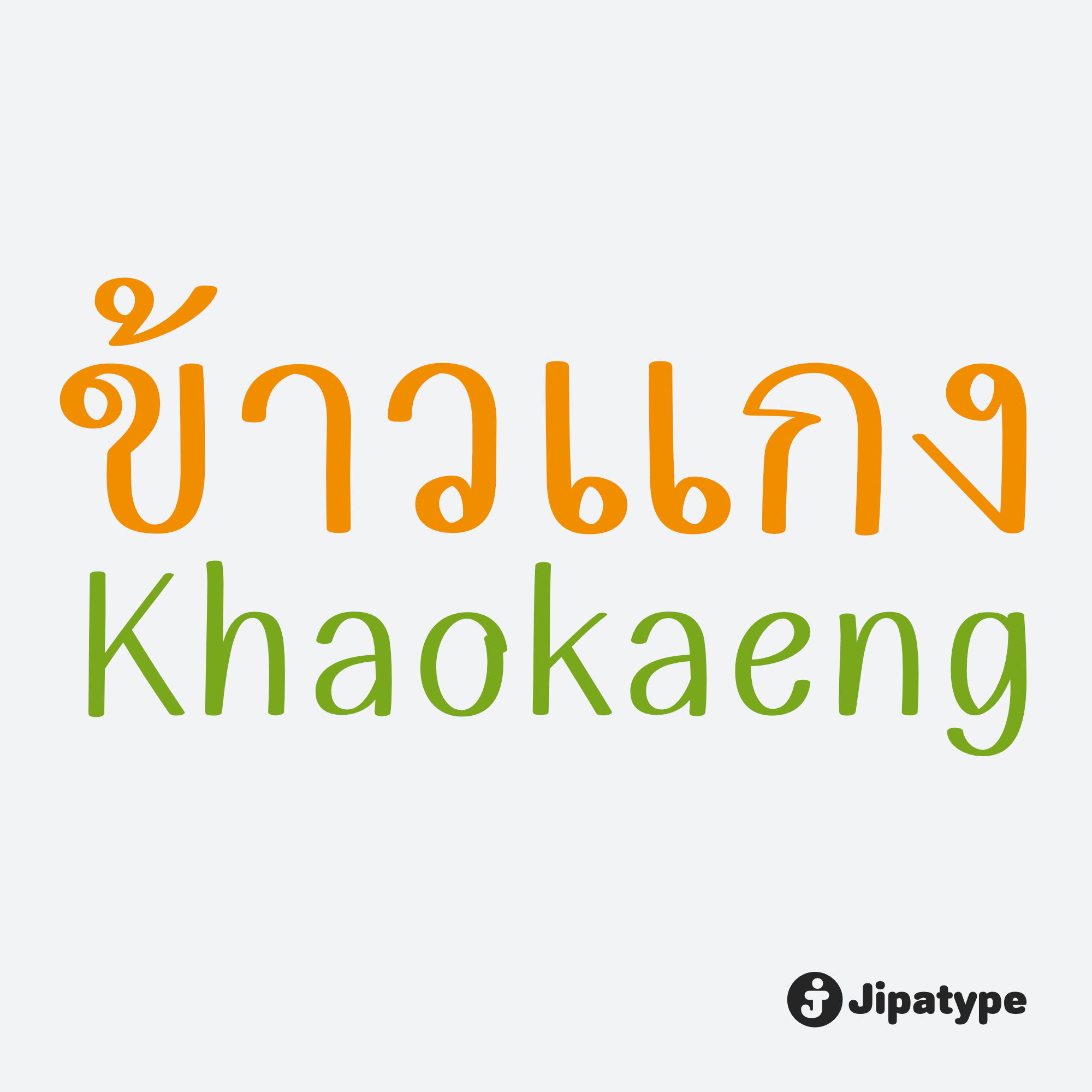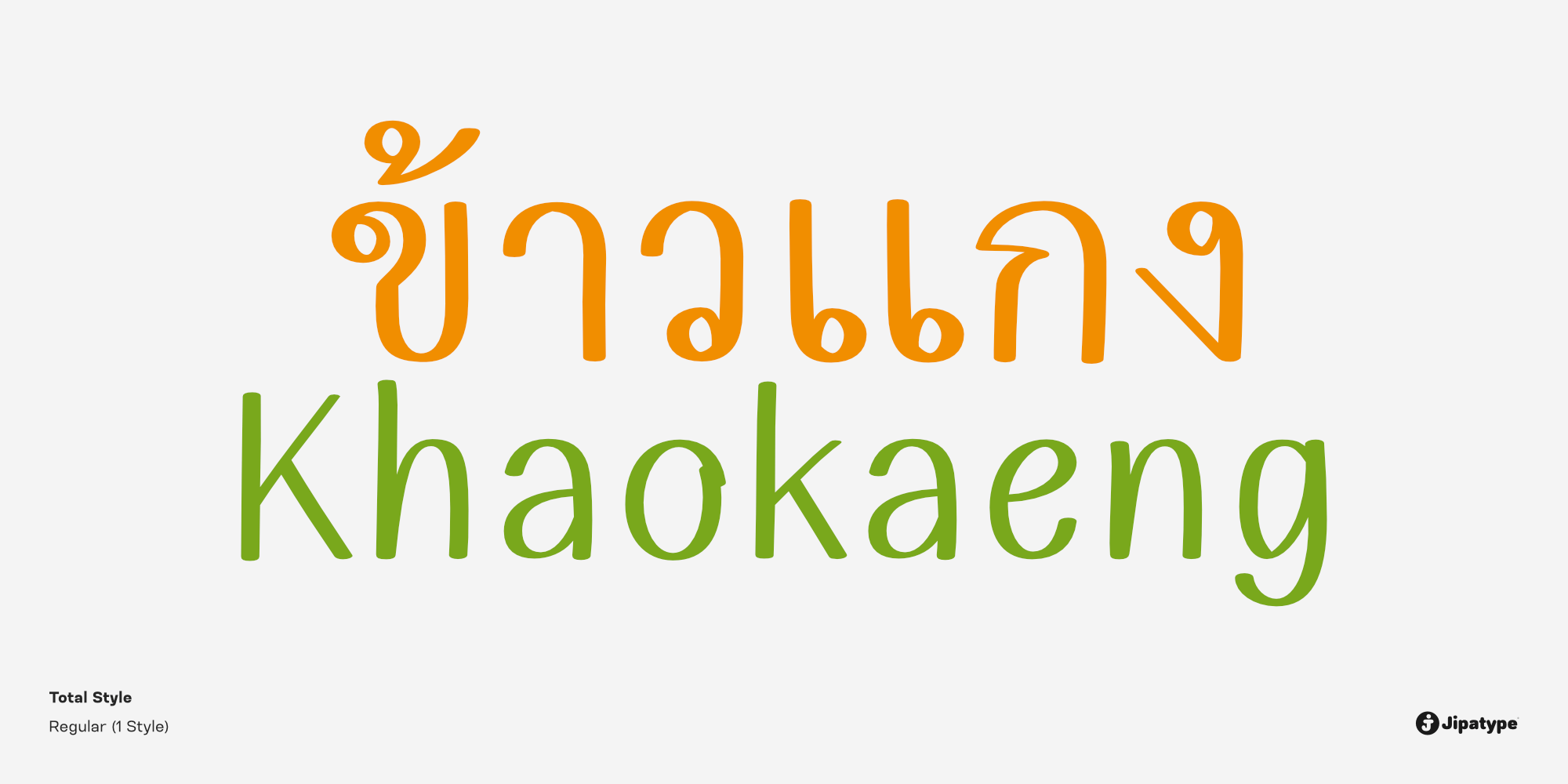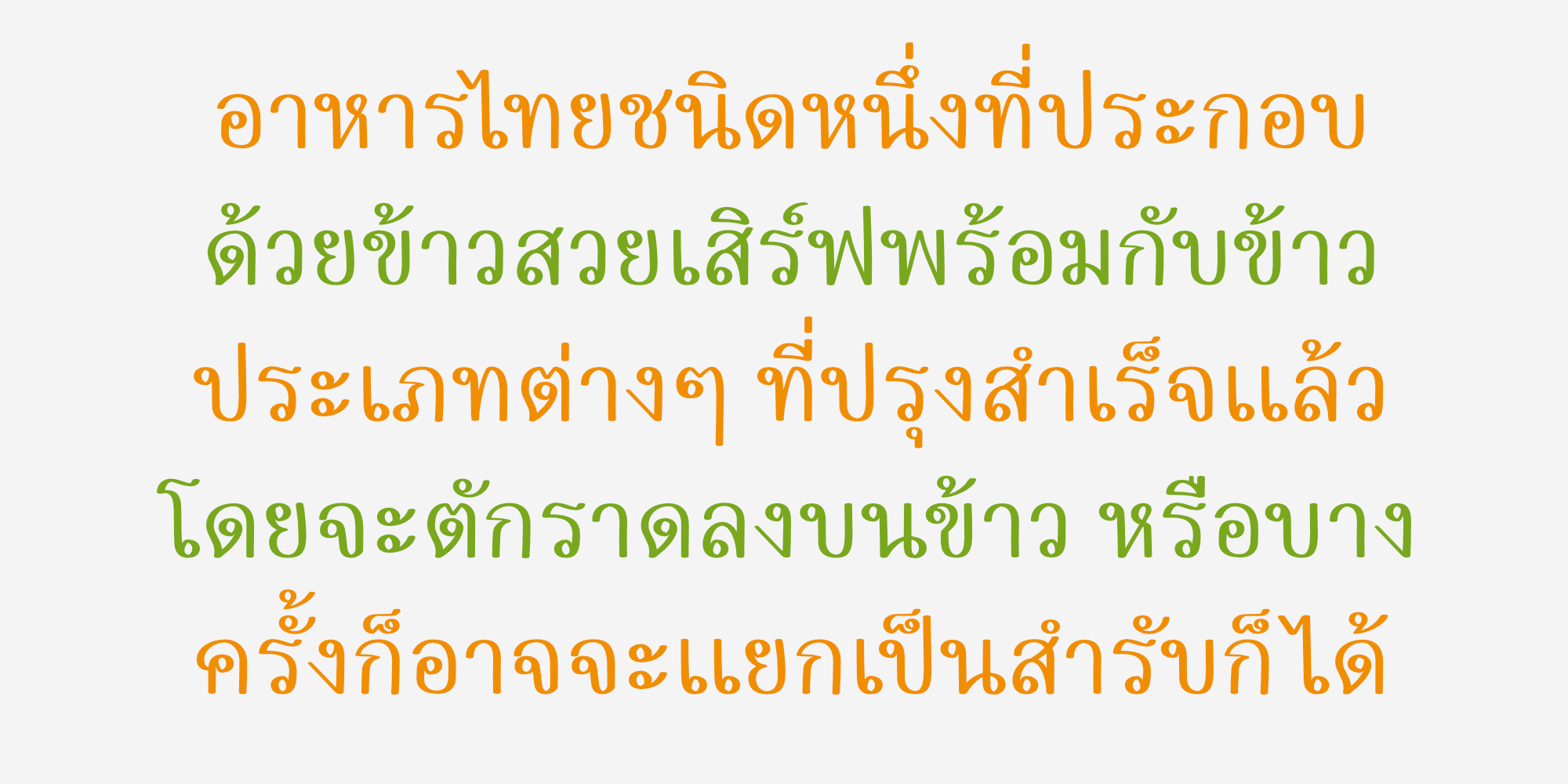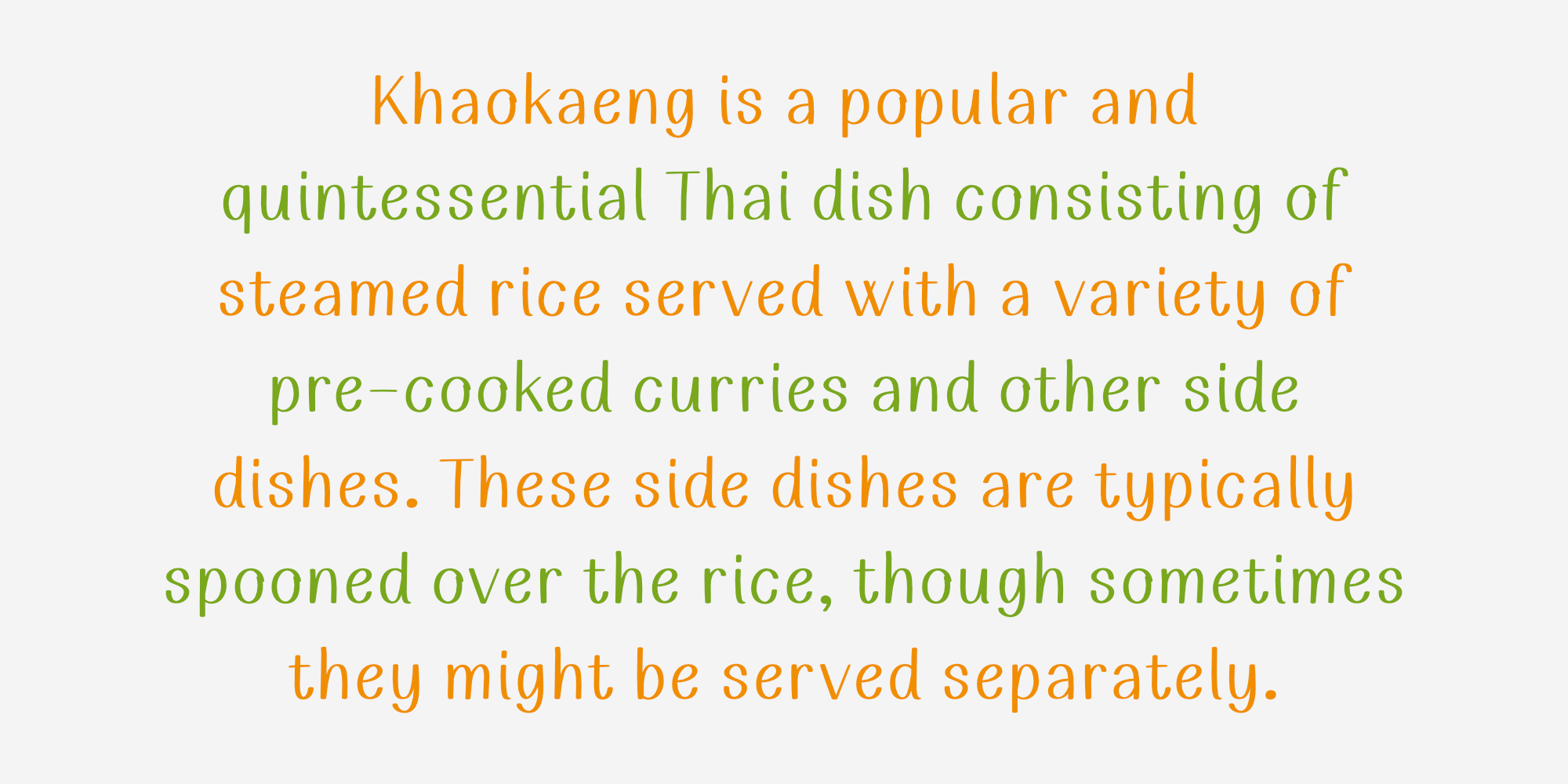
ข้าวแกง | Khaokaeng
Khaokaeng เป็นฟอนต์สไตล์ลายมือที่ให้ความรู้สึกเป็นกันเอง สนุกสนาน และอบอุ่น เหมือนเขียนด้วยปากกาเมจิกหัวตัด ที่มีดีไซน์เน้นความโค้งมนที่นุ่มนวลและมีความยืดหยุ่นเป็นธรรมชาติ ตัวอักษรไทยเป็นแบบมีหัวที่ชัดเจนแต่ออกแบบให้ดูทันสมัยและไม่เป็นทางการจนเกินไป เข้าคู่กับตัวอักษรละตินแบบ Sans-serif ที่มีบุคลิกขี้เล่นและอ่านง่าย
ด้วยรูปลักษณ์ที่ดู “น่ารัก” และ “เข้าถึงง่าย” นี้เอง ทำให้ฟอนต์ Khaokaeng เหมาะอย่างยิ่งสำหรับการนำไปใช้ในงานออกแบบที่ต้องการบรรยากาศผ่อนคลายและเป็นมิตร เช่น การทำเมนูอาหารและเครื่องดื่ม บรรจุภัณฑ์ขนม สื่อโฆษณาบนโซเชียลมีเดีย หนังสือเด็ก หรืองานคราฟต์ DIY ที่ต้องการสื่อสารด้วยความจริงใจและมีชีวิตชีวา